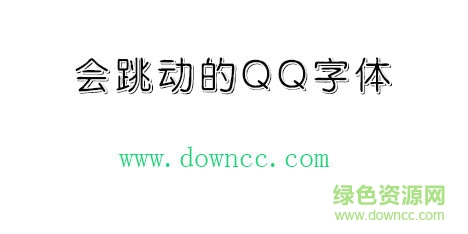
會(huì)跳動(dòng)的qq字體是一款qq會(huì)跳動(dòng)的字體哦,酷炫的閃動(dòng)字體可以讓您和您的朋友在聊天中,逼格瞬間提高,聊天更逗比哦,您還在等什么?喜歡就來下載體驗(yàn)唄,讓在聊天時(shí)字體更加炫彩奪目,你可別錯(cuò)過了這款免費(fèi)的qq字體哦。